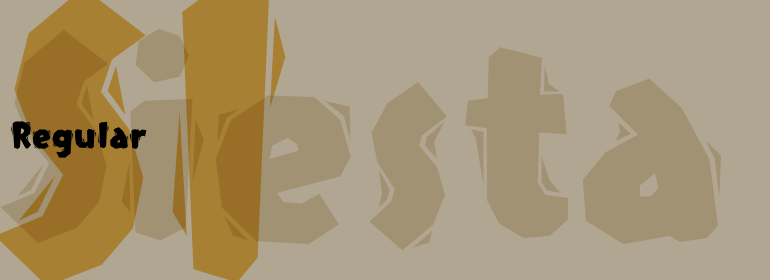
Siesta
Siesta,这款字体结构工整、笔画清晰,兼顾美观与易读性,适用于标题、正文、海报、包装、LOGO 等多种场景。字形优雅稳定,风格百搭耐看,适配日常排版与创意设计,让文字呈现更舒适、更具质感。Siesta一笔一画,皆是细节,以均衡的比例、流畅的线条打造舒适视觉体验,字形端正大气,风格简约现代。无论是商业设计、品牌宣传还是日常排版,都能轻松驾驭,让文字更有格调与力量。Siesta字体下载。